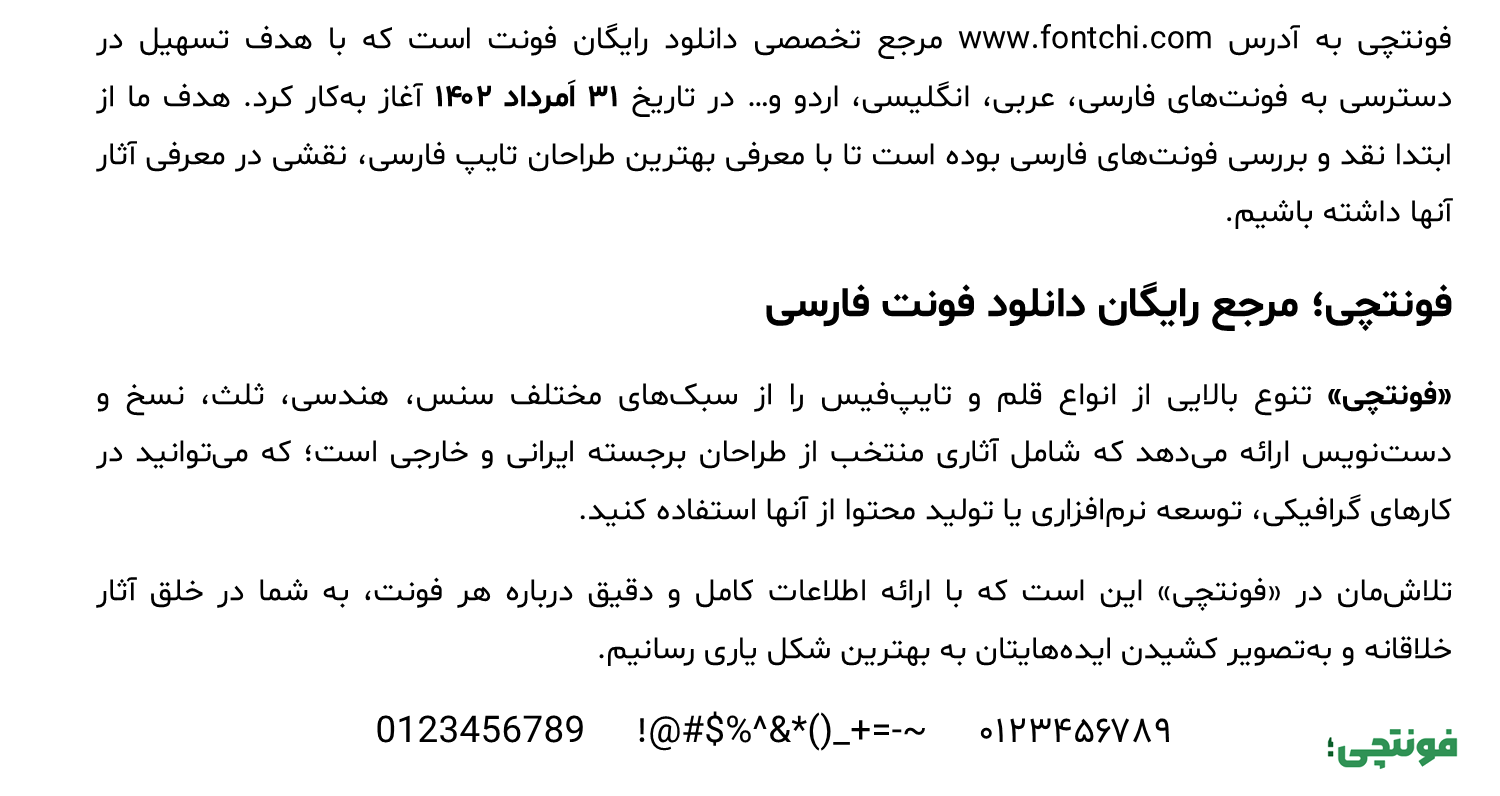
فونت شبنم (Shabnam)
فونت شبنم (به انگلیسی: Shabnam) از سری فونتهای رایگان مناسب متن است که از این قلم میتوانید برای فونت متون بلند در مطبوعات، صفحات وب، اپلیکیشن موبایل و فونت چاپ کتاب و مجلات استفاده کنید. این فونت دارای ظاهری نرم است که بر اساس خط نسخ طراحی شده است.
فونت رایگان شبنم توسط زندهیاد صابر راستی کردار طراحی شده است که ایده طراحی آن برگرفته از فونت رایگان وزیرمتن بوده است که خود برگرفته از فونت دژاوو است.
در ادامه این نوشته از سایت فونتچی به نقد و بررسی فونت شبنم خواهیم پرداخت؛ قلمی با سبک طراحی نسخ و بسیار نرم که خوانایی خوبی برای استفاده در متون بلند، بهویژه در حوزه کتاب و کتابخوانی دارد.
فونت شبنم رایگان از زبانهای فارسی، عربی و انگلیسی پشتیبانی میکند. به لطف رسم خط فارسی که سایر زبانهای خاورمیانهای مانند اردو، کوردی و بسیاری گویشهای محلی ایرانی مثل مازنی، بلوچ و… دارند از این قلم میتوانید استفاده چند زبانه داشته باشید.
برای حروف لاتین انگلیسی از فونت Roboto استفاده شده است بدون اینکه تغییراتی روی آن اعمال شده باشد. همچنین در بخش اعداد نیز شاهد گلیف استاندارد فارسی و عربی هستیم. مطابق با زبان صفحه کلید اعداد تایپ خواهند شد؛ بدین معنی که اعداد فارسی مثل «۴۵۶» با ظاهر متفاوت در عربی بهصورت «۴۵۶» تایپ خواهند شد و کمبودی از این بابت نخواهید داشت.
پیش نمایش و وزنهای فونت شبنم
فونت شبنم رایگان در ۵ وزن مختلف طراحی شده است. شامل نسخه نازک(Thin)، سبک(Light)، معمولی(Regular)، متوسط(Medium) و ضخیم(Bold) که تمامی این وزنها برای استفاده در متون بلند کاربرد دارند.
از این فونت نمیتوان انتظار زیادی برای استفاده در عناوین داشت. هرچند که با انتخاب سایز بزرگتر میتوان این نیاز را برطرف کرد، ولی توصیه میشود بهجای آن از قلم نزدیکتری مثل فونت ایران یکان استفاده کنید.
طراحی حروف در فونت شبنم تا حدودی کمی دارای ارتفاع فشرده است که حروف نیز کمی کشیده بهنظر میرسند. همین عامل سبب شده تا فاصلهگذاری کلمات کمی از هم بیشتر باشد تا به خوانایی متن کمک کند. خصوصا در متون بلند مانند متن کتاب و مجلات که کاربر برای جلوگیری از خستگی چشم نیاز دارد از چنین فونتی استفاده کند.
این فونت رایگان برای کپ کات با توجه به پشتیبانی که از وزن Bold دارد میتواند انتخاب خوبی باشد تا از آن برای طراحی کاور ویدئوهای خود استفاده کنید.
ظاهر حروف نیز ساختاری نسبتا گرد دارد و بهشکل رسمی طراحی شدهاند. ایجاد چنین منحنیهایی در حروفی مثل «س، ش، ل، ن» بیشتر خودنمایی میکند. طوری که نسبت به خط کرسی نزدیکتر هستند و همین عامل آن را به قلمی فشرده تبدیل کرده است.
کاربردهای فونت shabnam
با توجه به ویژگیهایی که برای فونت شبنم اشاره کردیم، استفاده از این قلم برای متون بلند کاربردی است. از جمله رایجترین کاربردهایی که این قلم دارد میتوان به صنعت چاپ اشاره کرد که بسیاری از کتب، مجلات و روزنامهها با این فونت چاپ میشوند.
از سوی دیگر این فونت دارای ظاهری رسمی مشابه با فونت های سری B است مانند فونت بی یکان یا بی کودک است؛ با این تفاوت که میتوان آن را نسخهای متمایز و حرفهایتر از آنها قلمداد کرد. بهویژه اینکه از سایر زبانها پشتیبانی کاملتری داشته و امکان تایپ اعداد نیز متناسب با هر زبان فراهم است.
این فونت همچنین برای استفاده در اپلیکیشنهای موبایل کاربرد دارد. میتوانید با دانلود فونت شبنم برای کپ کات از این قلم برای تهیه تامنیل ویدئوها یا پوستر شبکههای اجتماعی نیز بهره ببرید. بهطور کلی shabnam فونت خوبی برای کاربردهایی است که با متون کوتاه و بلند سر و کار داشته باشیم.